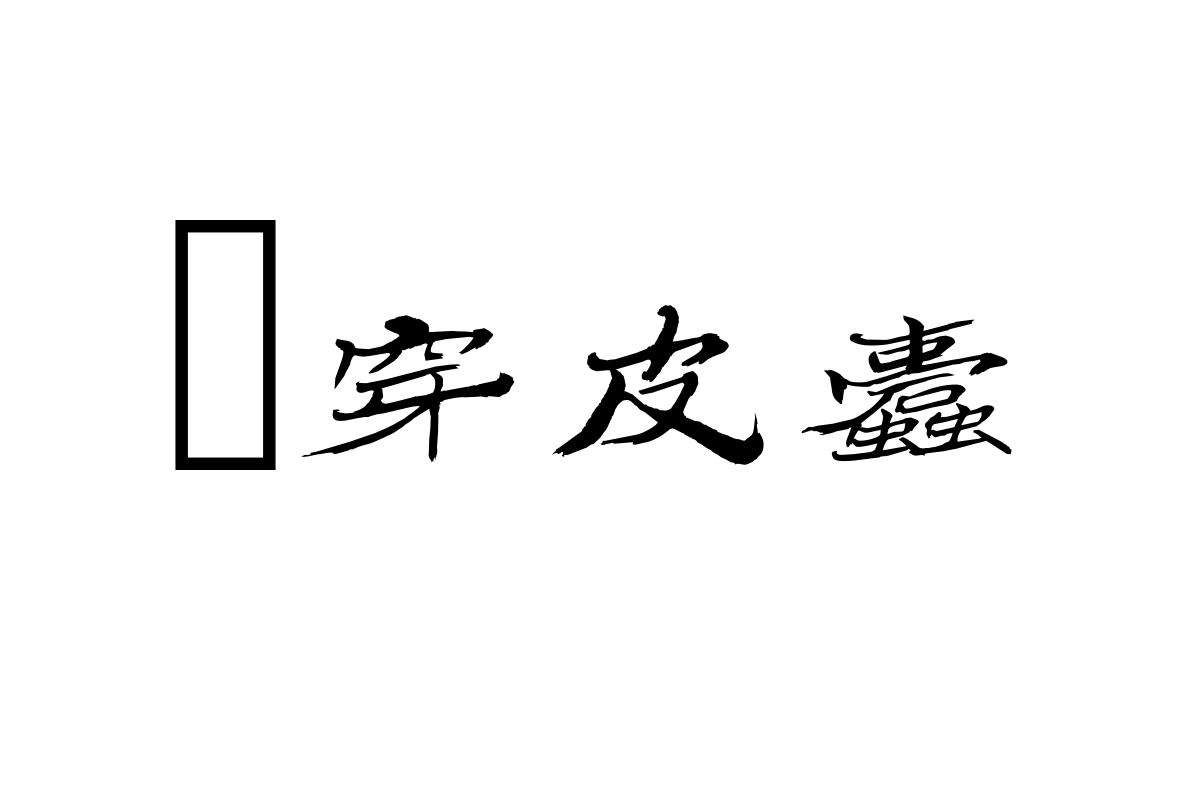
汉仪铁山隶书简是一种具有中国传统书法特色的字体,它源自汉代的隶书风格。这种字体的特点是笔画粗细变化较大,线条流畅而有力,具有很强的视觉冲击力。
在设计中,汉仪铁山隶书简可以用于标题、正文等需要强调文字的部分,也可以作为装饰元素使用,增加设计的美感和艺术感。它的应用范围非常广泛,包括广告设计、包装设计、网页设计等领域。